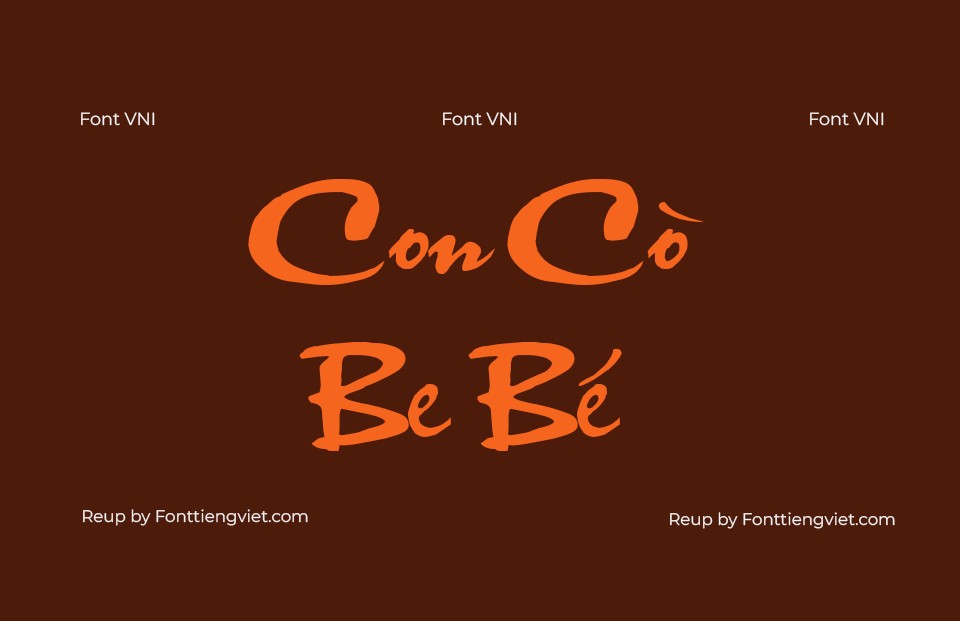
Trong thời đại kỹ thuật số, việc tìm kiếm những phông chữ mang đậm bản sắc văn hóa dân tộc luôn là ưu tiên hàng đầu của các nhà thiết kế và đặc biệt là học sinh, sinh viên khi thực hiện các dự án học thuật. Một Font Chữ đẹp không chỉ truyền tải nội dung mà còn gửi gắm tinh thần nghệ thuật. Và đó chính là lý do Font Việt hoá VNI Thuphap1 trở nên phổ biến. Đây không chỉ là một phông chữ; nó là một tác phẩm thư pháp được số hóa, mang lại sự mềm mại, uyển chuyển của nét bút lông truyền thống vào các tài liệu, ấn phẩm hiện đại của bạn. Dù bạn đang làm báo tường cho trường học, thiết kế thiệp chúc Tết, hay chỉ đơn giản là muốn làm mới giao diện bài thuyết trình của mình, VNI Thuphap1 chắc chắn sẽ là lựa chọn không thể thiếu, giúp dự án của bạn nổi bật giữa đám đông.
Font Việt hoá VNI Thuphap1: Điểm Nhấn Nghệ Thuật Cho Thiết Kế Của Bạn
Font Việt hoá VNI Thuphap1 thuộc nhóm font thư pháp (Calligraphy font), mô phỏng lại những nét chữ bay bổng, phóng khoáng của nghệ thuật viết thư pháp truyền thống Việt Nam. Điều làm nên sự đặc biệt của phông chữ này chính là khả năng hiển thị tiếng Việt hoàn chỉnh. Rất nhiều font thư pháp đẹp trên thế giới không hỗ trợ tiếng Việt, gây khó khăn cho người dùng trong nước. Tuy nhiên, phiên bản Việt hóa của VNI Thuphap1 đã giải quyết triệt để vấn đề này, đảm bảo rằng mọi dấu câu, dấu thanh đều được thể hiện một cách tinh tế và hài hòa, không làm mất đi vẻ đẹp vốn có của nét chữ thư pháp. Sự kết hợp giữa tính thẩm mỹ cao và khả năng tương thích ngôn ngữ đã biến VNI Thuphap1 thành công cụ không thể thiếu trong bộ sưu tập font của mọi designer và học sinh chuyên nghiệp.
So với các phông chữ tiêu chuẩn như Times New Roman hay Arial, VNI Thuphap1 mang lại sự khác biệt lớn về mặt cảm xúc. Trong khi các font chuẩn tạo ra cảm giác trang trọng, nghiêm túc, thì VNI Thuphap1 lại khơi gợi sự hoài cổ, tính nghệ thuật và sự khéo léo. Các nét thanh, nét đậm được phân bổ hợp lý, tạo ra sự nhịp điệu và dòng chảy tự nhiên. Đặc biệt, nó rất phù hợp với các chủ đề liên quan đến lịch sử, văn hóa dân gian, hoặc các sự kiện truyền thống như Tết Nguyên Đán hay lễ kỷ niệm. Đối với các bài tập lớn hoặc luận văn tốt nghiệp cần sự phá cách nghệ thuật, việc sử dụng VNI Thuphap1 cho tiêu đề hoặc trích dẫn quan trọng sẽ tăng thêm giá trị thị giác đáng kể.
Ứng Dụng Đa Dạng Của Phông Chữ Thư Pháp
Trong Giáo Dục và Dự Án Học Đường
Học sinh và sinh viên thường xuyên phải đối mặt với các dự án cần tính sáng tạo cao. Các dự án làm báo tường, thiết kế thiệp mời cho các sự kiện của trường, hay làm kỷ yếu cuối năm là nơi lý tưởng để phông chữ thư pháp này tỏa sáng. Phông chữ thư pháp VNI Thuphap1 giúp các bạn trẻ thể hiện sự tôn trọng đối với nét đẹp văn hóa truyền thống. Khi làm báo tường chủ đề về quê hương, đất nước, hoặc các bài thuyết trình về thời kỳ phong kiến, việc sử dụng chữ viết tay mô phỏng này sẽ tạo ra ấn tượng sâu sắc và chuyên nghiệp hơn rất nhiều so với các font thông thường. Đây cũng là một cách tuyệt vời để các em học sinh trung học thể hiện sự khéo léo và gu thẩm mỹ của mình trong các cuộc thi sáng tạo.
Trong Thiết Kế Đồ Họa và Marketing
Không chỉ giới hạn trong môi trường học thuật, phông chữ VNI này còn được các nhà thiết kế đồ họa chuyên nghiệp ưu ái. Nó thường xuyên xuất hiện trên các bao bì sản phẩm mang tính thủ công, các thương hiệu trà, cà phê truyền thống, hay các ấn phẩm quảng cáo cho dịp lễ hội. Khả năng truyền tải tính “Việt” mạnh mẽ làm cho VNI Thuphap1 trở thành một công cụ marketing hiệu quả, giúp thương hiệu dễ dàng kết nối với cảm xúc của khách hàng. Việc sử dụng font chữ thư pháp trong logo hoặc slogan sẽ ngay lập tức tạo ra sự độc đáo và khác biệt, tránh sự nhàm chán của các kiểu chữ sans-serif hiện đại. Các designer chuyên nghiệp thường kết hợp VNI Thuphap1 với các họa tiết cổ điển để tối đa hóa hiệu ứng thị giác.
Tóm lại, Font Việt hoá VNI Thuphap1 là sự lựa chọn hoàn hảo cho bất kỳ ai muốn kết hợp sự tinh tế của nghệ thuật thư pháp truyền thống vào các sản phẩm kỹ thuật số. Từ các bạn học sinh trung học đang chuẩn bị cho các kỳ thi tốt nghiệp với những dự án văn hóa, đến các nhà thiết kế đang tìm kiếm phông chữ độc đáo cho thương hiệu của mình, VNI Thuphap1 luôn mang lại giá trị thẩm mỹ vượt trội. Việc đầu tư thời gian tìm hiểu và sử dụng loại phông chữ đặc biệt này sẽ nâng tầm chất lượng thị giác của bạn lên một bậc. Hãy bắt đầu trải nghiệm sự độc đáo mà phông chữ này mang lại ngay hôm nay để thấy sự khác biệt. Đừng quên rằng, việc lựa chọn một Font Chữ phù hợp chính là bước đầu tiên để tạo nên một tác phẩm nghệ thuật số ấn tượng và giàu cảm xúc.